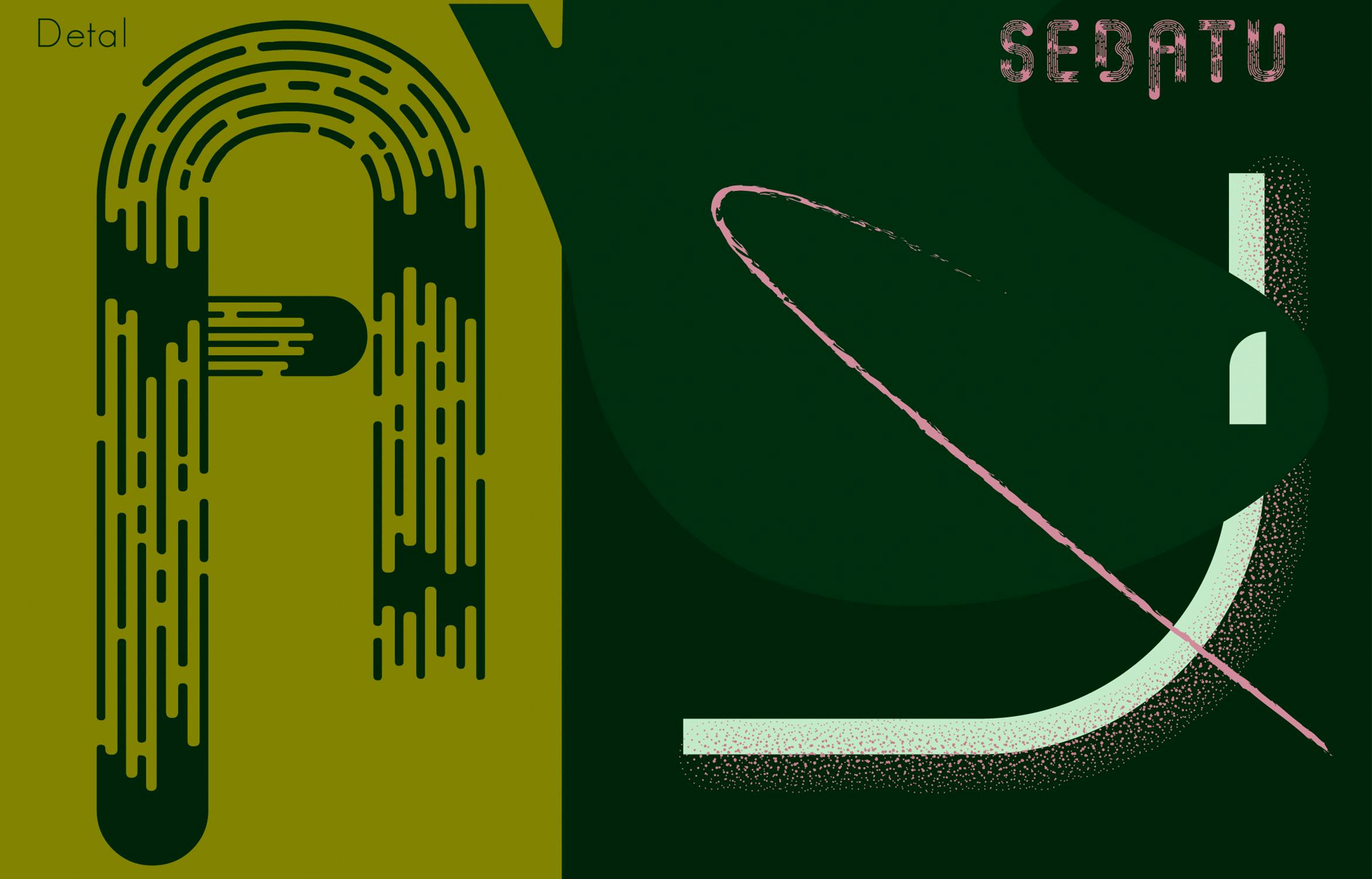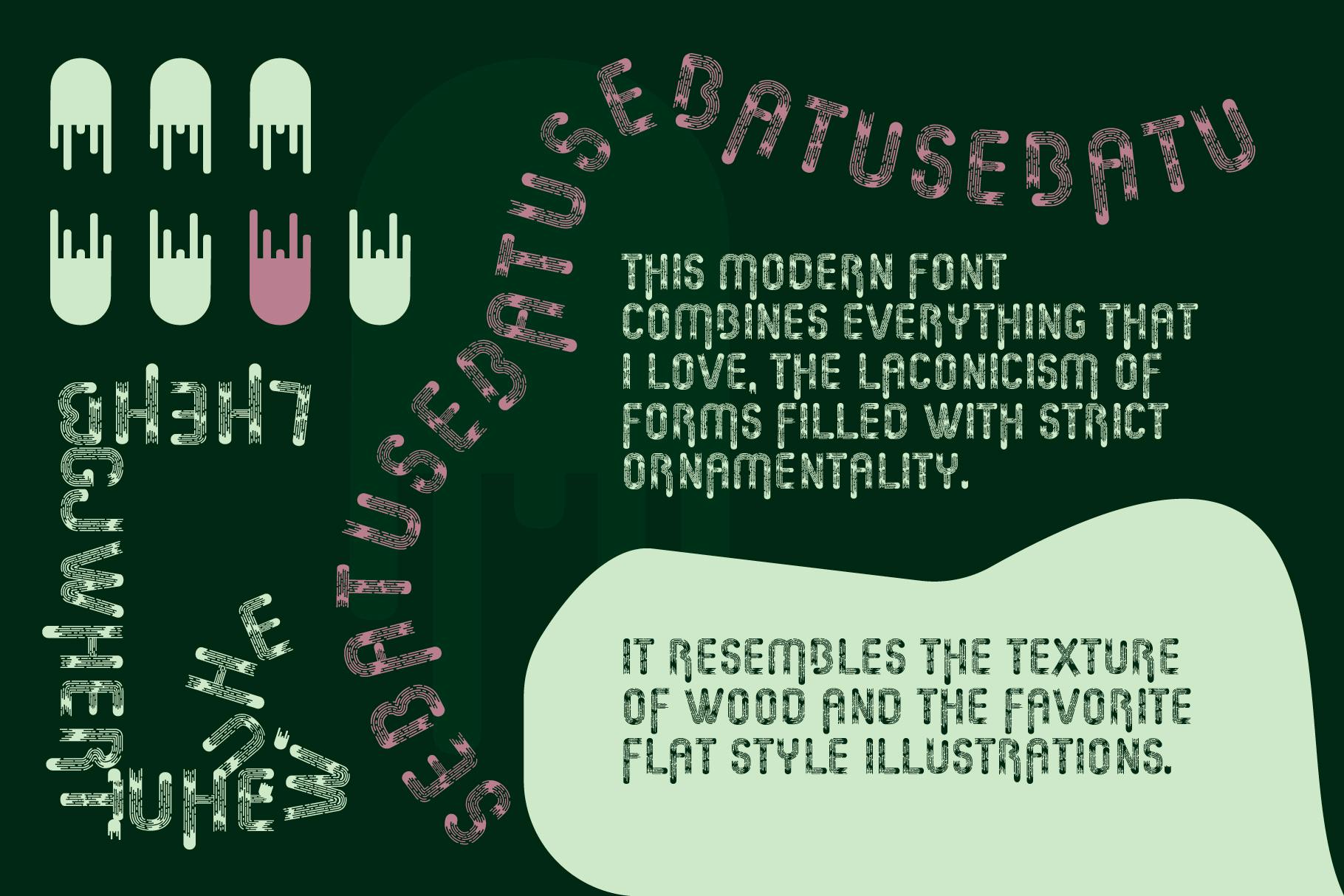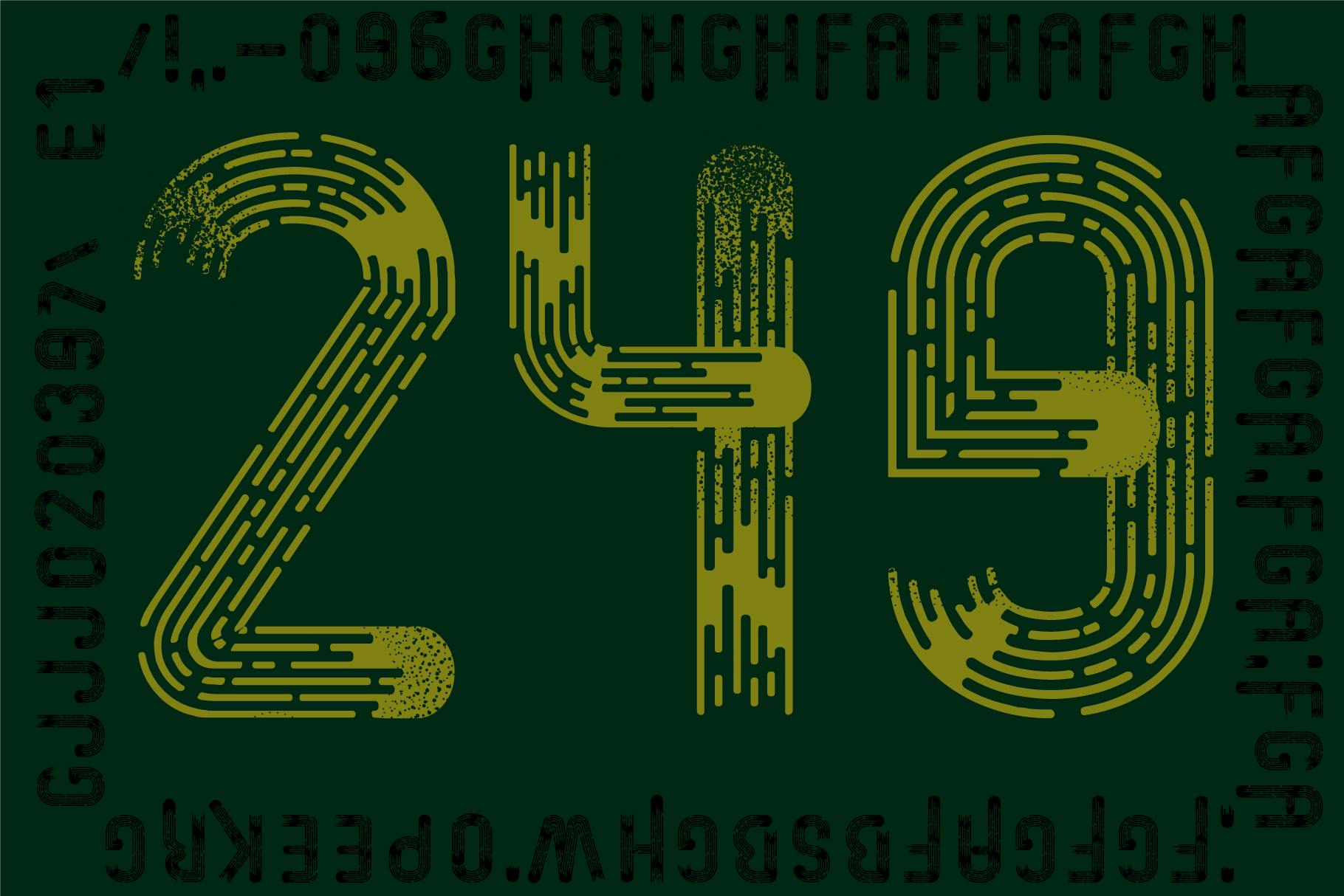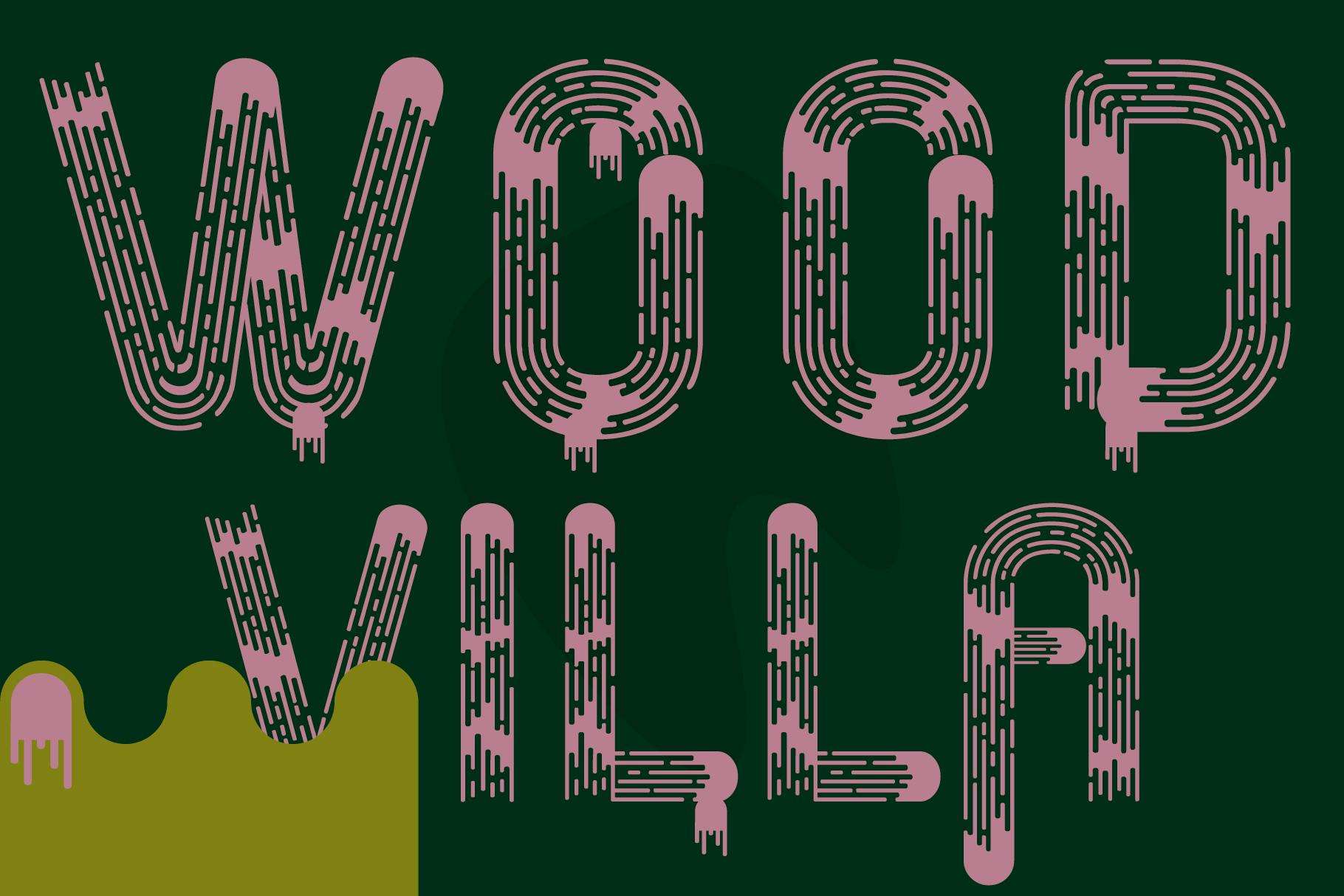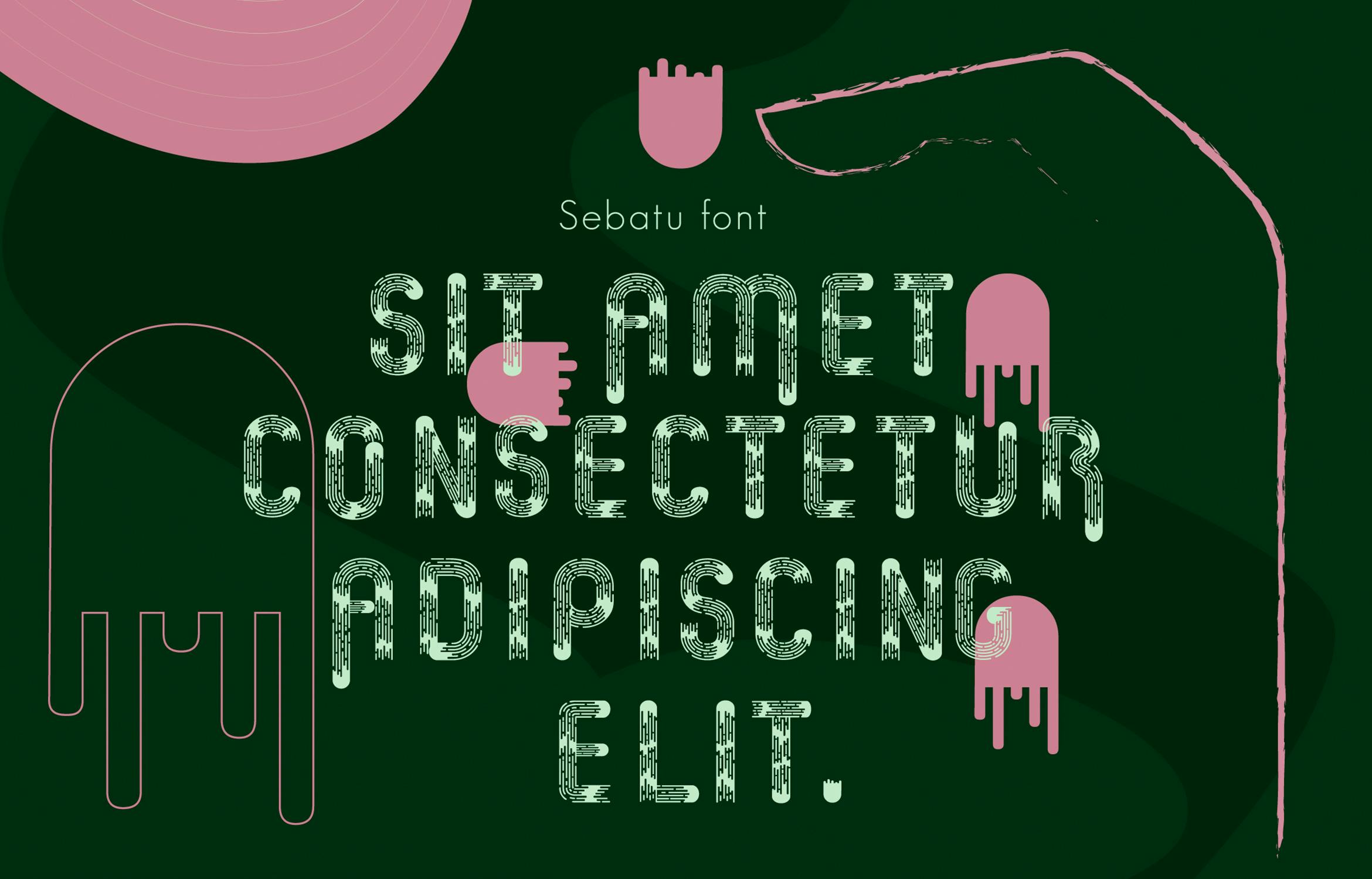
این فونت مدرن ترکیبی از همه چیزهایی است که من دوست دارم، سادگی اشکال همراه با تزئینات دقیق. این فونت شبیه به بافت چوب و سبک مسطح محبوب است. بدون شک در طراحی، اصالت و خودکفایی خود را به نمایش میگذارد.